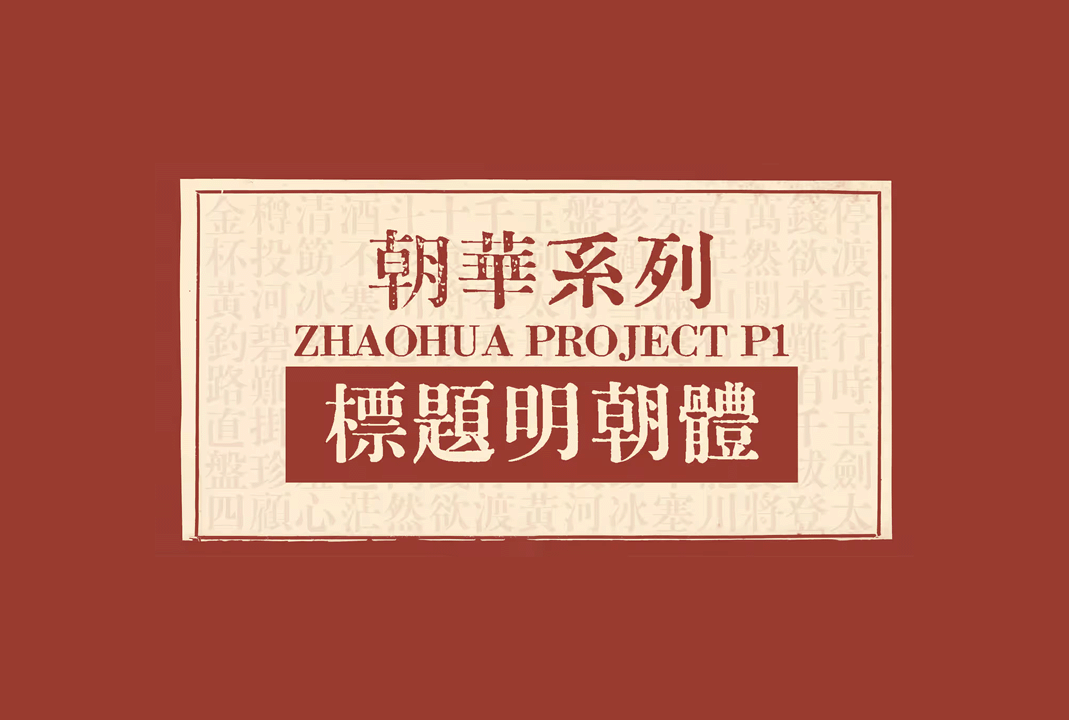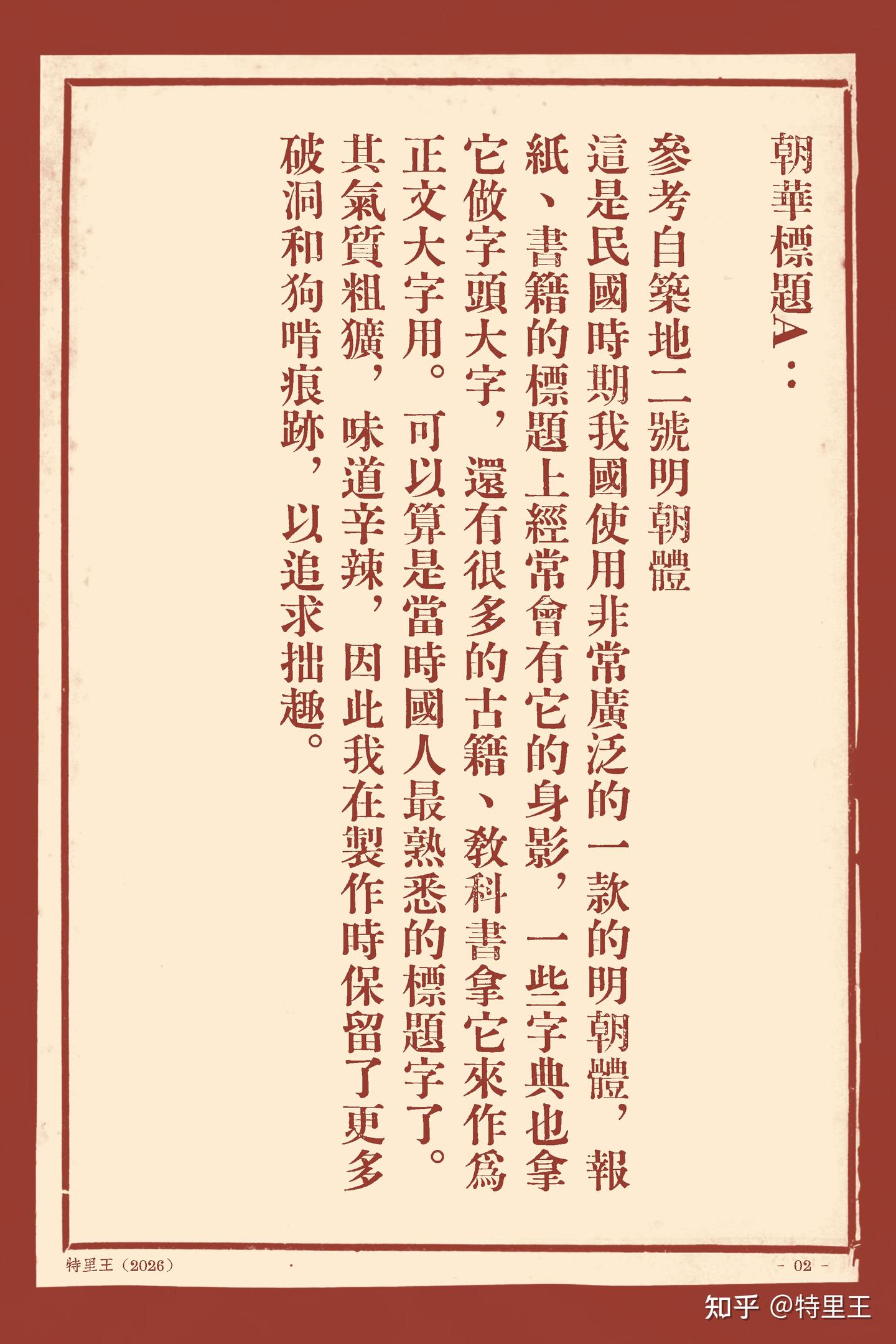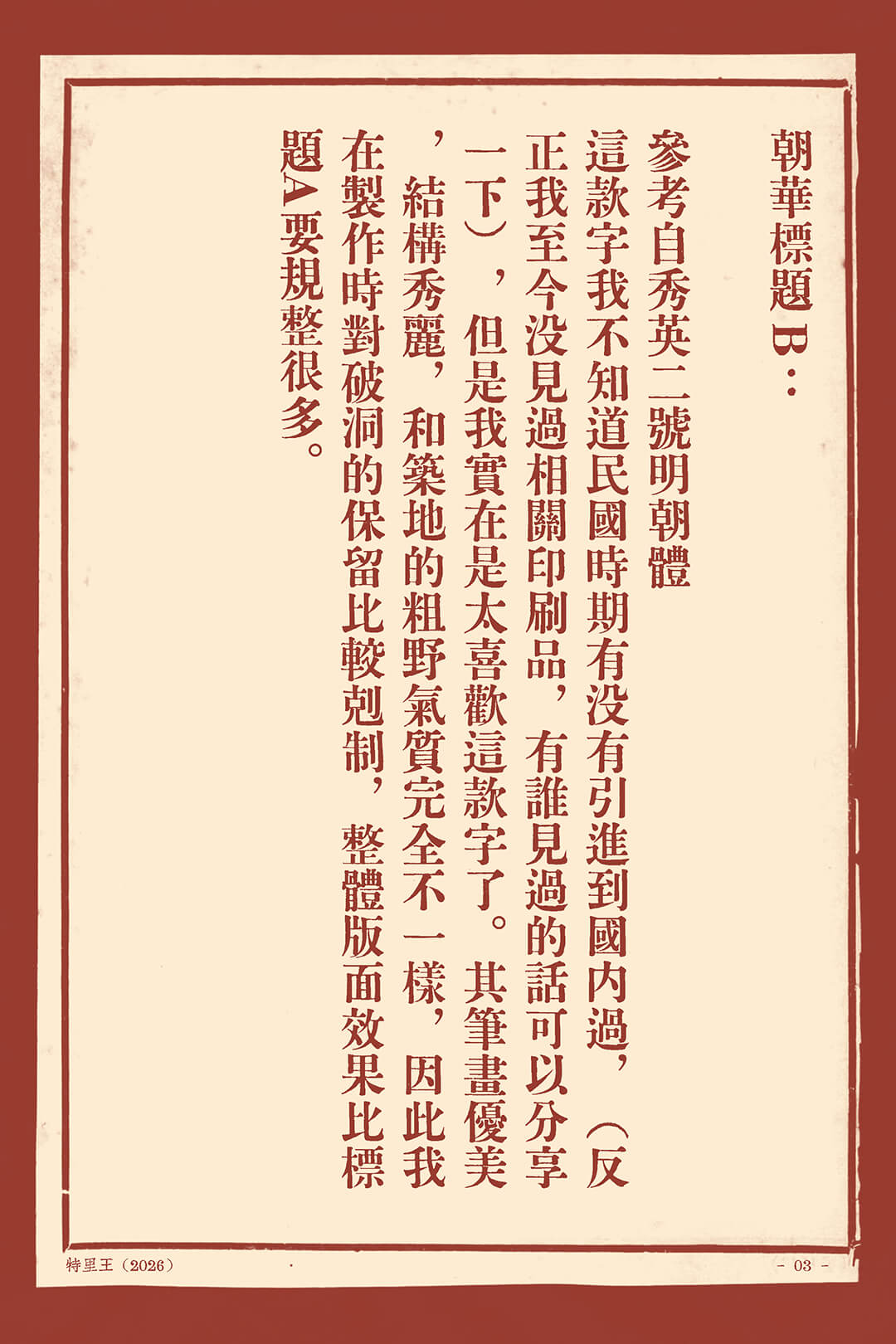
标题明朝体[朝华标题A+朝华标题B]_免费商用中文字体下载
标题明朝体[標題明朝体]是特里王制作发布的朝华系列字体中的一款免费可商用字体,包含两个字体:朝华标题A、朝华标题B。
朝华系列是汇文系列的查漏补缺,旨在进一步丰富复古印刷字体的品类。
标题明朝体——朝华标题A 参考自筑地二号明朝体
标题明朝体——朝华标题B 参考自秀英二号明朝体